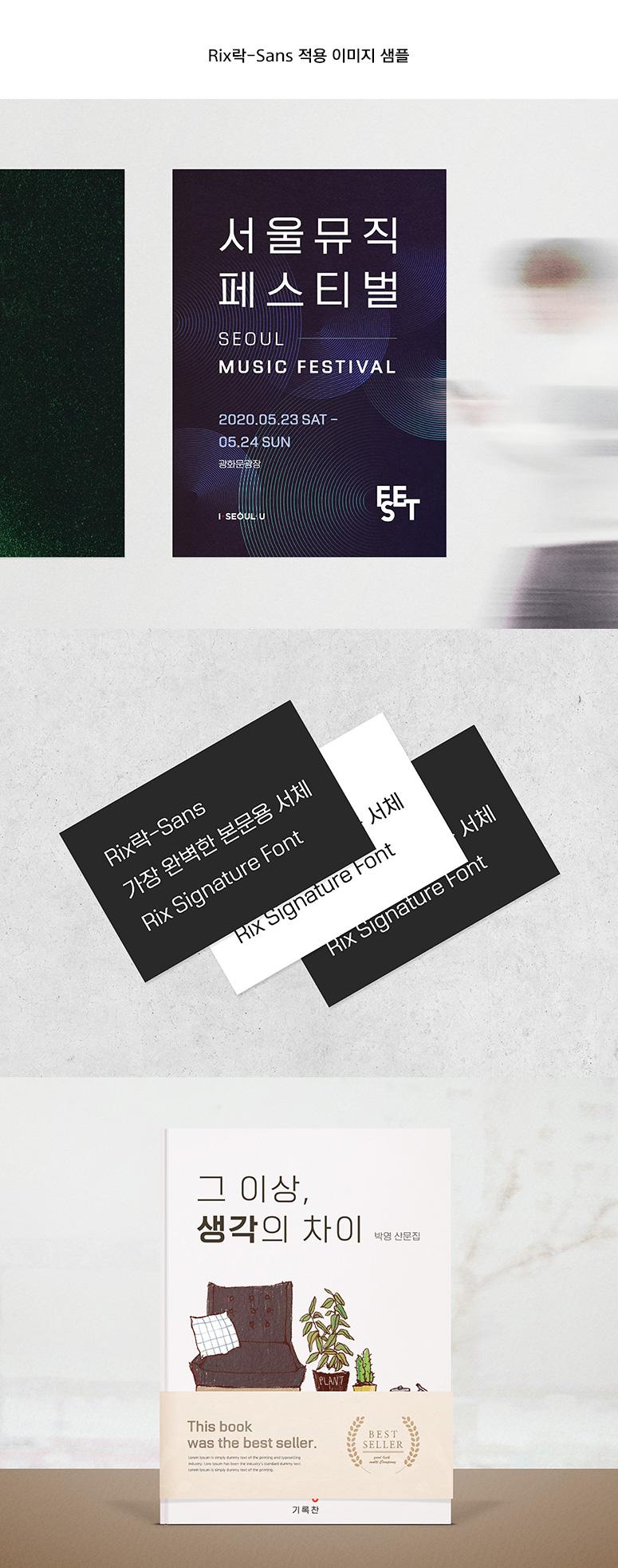
Rix락-Sans
9 종 - Black, Heavy, Extra Bold, Bold, Semi Bold, Medium, Regular, Light, Ultra Light
Rix락-Sans는 네모 꽉 찬 글자틀과 세련된 형태로 정갈하고 모던합니다.
일반적인 디자인의 자소로 담백하고 군더더기 없는 형태의 서체입니다.
어디에나 쉽게 적용할 수 있도록 총 9가지의 굵기 제공으로 다양한 니즈를 충족합니다.